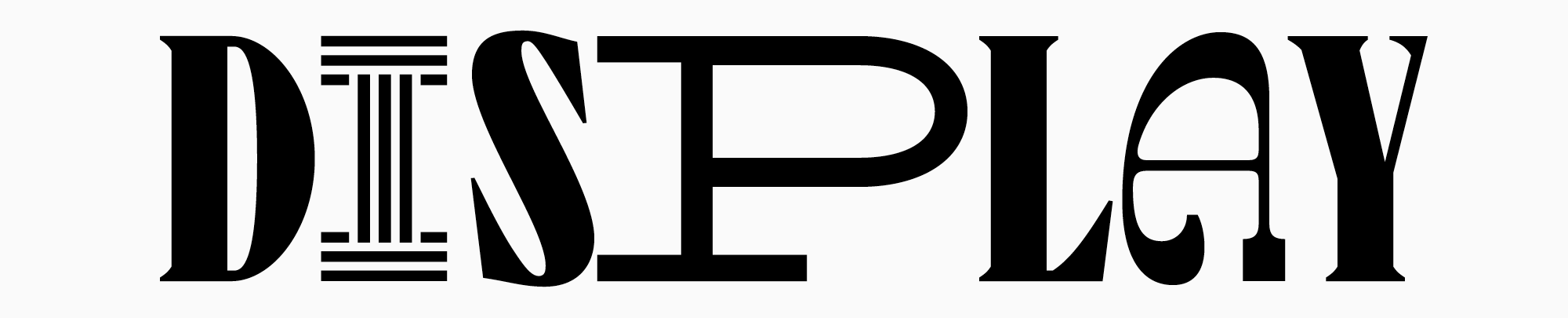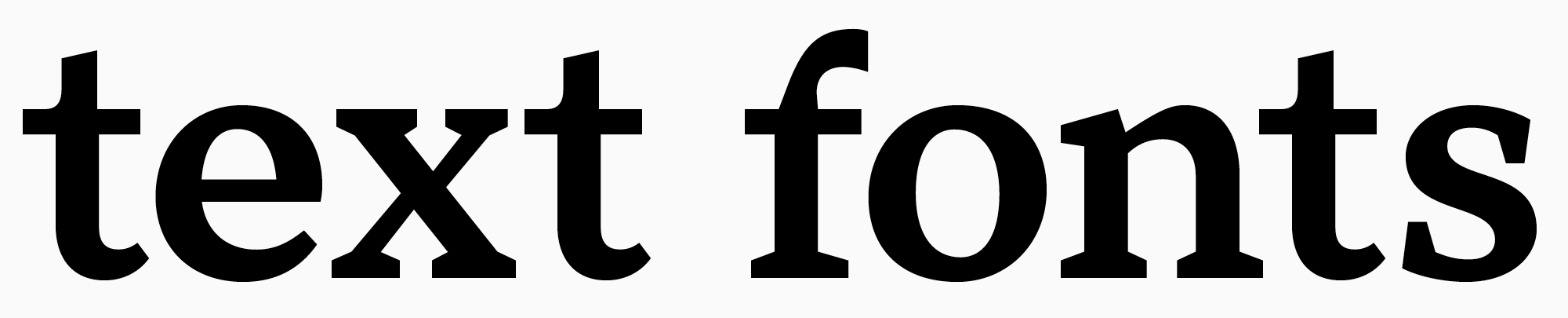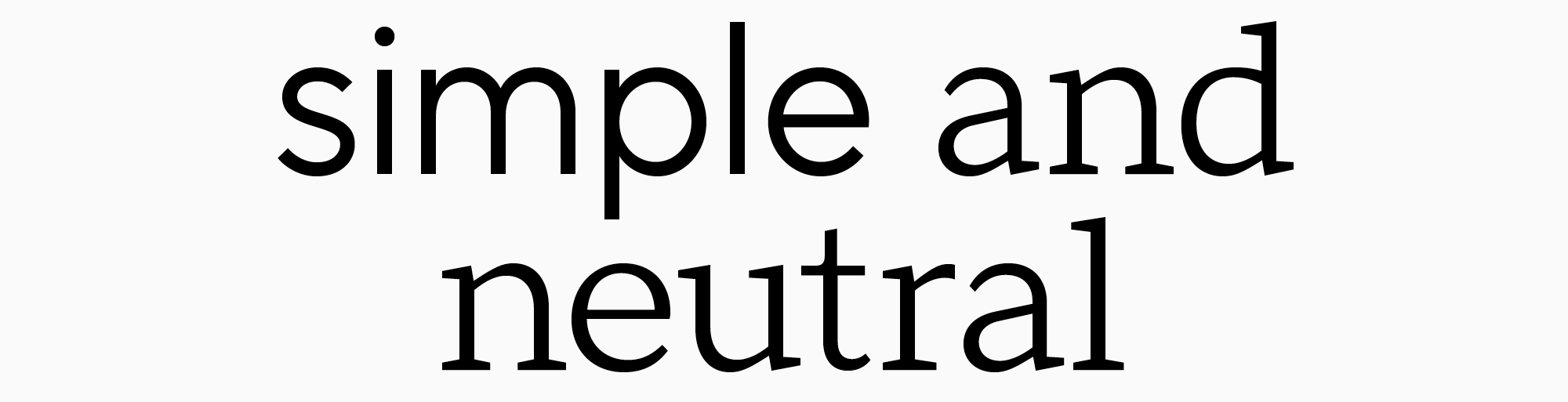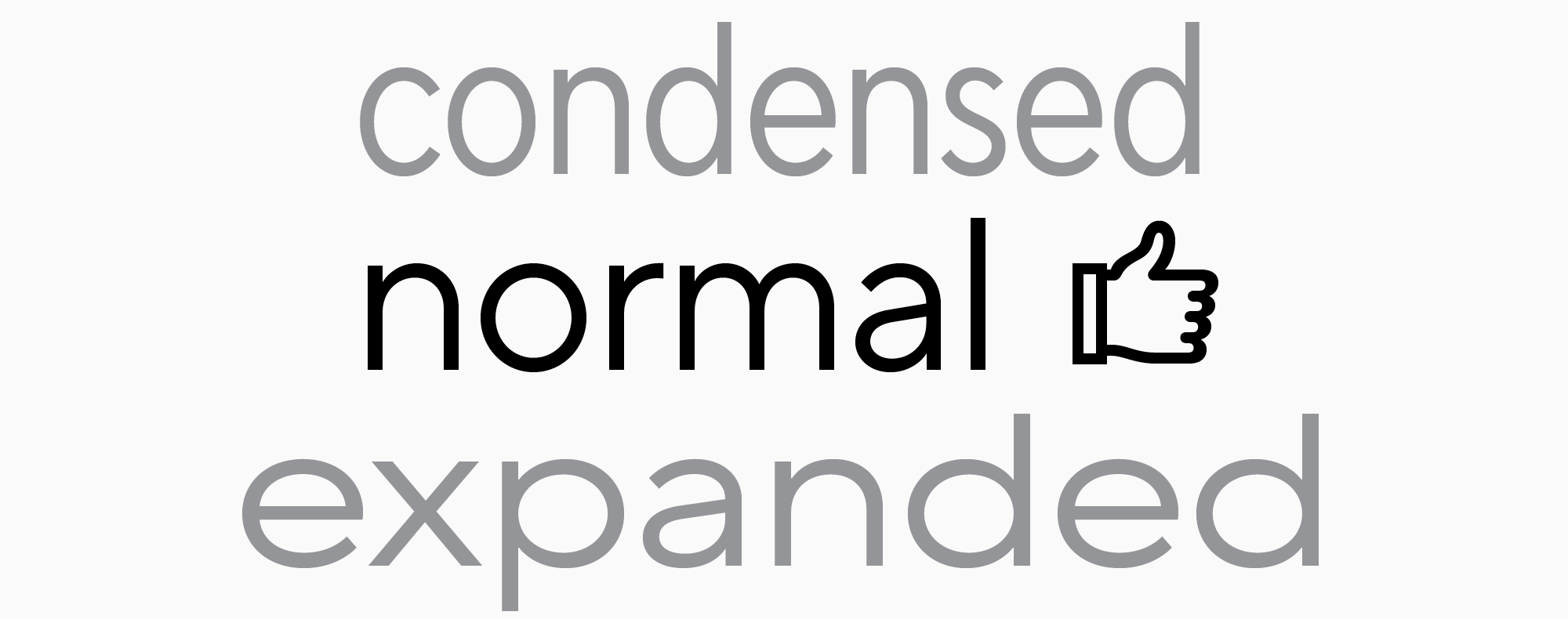
Какие шрифты лучше подходят для чтения? ТОП-10
Выбрать лучший шрифт для чтения — задача, которая возникает перед нами чаще, чем может показаться. Читабельный шрифт может понадобиться для масштабных проектов, таких как создание сайта, верстка книги или разработка мобильного приложения. Но также вопрос, какой шрифт выбрать для чтения, нередко возникает в более мелких, бытовых ситуациях: например, во время написания текста в «Ворд» и его печати на листе бумаги.
Какой шрифт наиболее удобен для чтения? От чего зависит читабельность шрифта? Какой шрифт лучше подойдет для чтения книг, а какие — для чтения с экрана? На эти и другие вопросы мы постарались ответить в этой статье.
Почему важно использовать удобные для чтения шрифты?
Представьте, что вы отправляете покупателю свой товар, в который вложили много сил. Вы красиво его упаковали и и обещали доставить как можно быстрее. Но курьер везет его очень долго, по пути роняет и пачкает. Содержание посылки остается неизменным, но покупатель тратит время и нервы на ожидание, а затем его впечатление окончательно портится при виде грязной, изорванной упаковки, которую он с трудом распаковывает. Скорее всего он больше не захочет ничего у вас заказывать.
И шрифт в этой аналогии — тот самый курьер. От него зависит, насколько легко и приятно пользователь будет воспринимать информацию, которую вы доносите до него с помощью текста. Одни шрифты будут читаться быстро и просто, другие — с трудом, отвлекая внимание от самой сути.
Это не значит, что одни шрифты однозначно хорошие, другие — однозначно плохие. Все зависит от того, где вы их используете: идеальный шрифт для баннера может не подойти для оформления веб-сайта, а лучший шрифт для верстки — оказаться неудачным для вывески.
Поэтому для начала давайте разберемся, какие шрифты лучше подходят для разных целей.
Какие шрифты лучше подходят для чтения?
Все шрифты по назначению можно разделить на акцидентные и текстовые.
Акцидентные отличаются ярким и выразительным характером, могут быть необычными и непривычными для глаза. Они привлекают к себе внимание и используются для акцентных надписей и заголовков (поэтому их часто называют заголовочными). Такие шрифты эффектно смотрятся в отдельных крупных надписях, но неудобны для массивов текста — глаз цепляется за отдельные буквы, мешая восприятию написанного. Они часто насыщены множеством деталей, которые интересно рассматривать в крупном кегле. В мелком же размере эти детали теряются, к тому же могут «размывать» буквы, делая текст грязным и трудно читаемым. Кроме того, обычно для них характерен высокий контраст, который делает их выразительными, но, опять же, менее читаемыми в маленьком кегле.
Текстовые же шрифты предназначены именно для набора больших массивов текста. Они более нейтральные и спокойные, оформлены лаконично, обладают низким контрастом и не имеют лишних деталей. Все это делает их более разборчивыми в мелком кегле и позволяет глазу легко скользить по тексту, не отвлекаясь на сами знаки. Кроме того, текстовые шрифты хорошо читаются в мелком кегле. Так что именно эта группа шрифтов нас сегодня интересует.
Существует представление о том, что шрифты без засечек лучше подходят для чтения, чем шрифты с засечками. Однако это не так: шрифты с засечками, или антиквы, вполне могут быть текстовыми, а засечки — помогать восприятию текста. Поэтому важно понимать, что же на самом деле влияет на читабельность шрифта.
Что делает шрифт удобочитаемым?
Здесь нужно разделить понятия «разборчивость» и «читабельность».
Когда мы говорим о разборчивости (legibility), имеется в виду четкость отдельных знаков и точность их начертания, которая влияет на легкость распознавания разных букв.
Читабельность (readability) же зависит от того, как знаки взаимодействуют между собой, то есть каким получается само тело текста при наборе. Это характеристика, указывающая на то, насколько удобно воспринимать массив текста.
В первую очередь, чтобы хорошо читаться, шрифт не должен быть сложным. Самый читабельный шрифт — простой и достаточно нейтральный. Излишние элементы будут размывать знаки в маленьком кегле, а слишком яркий характер может отвлекать внимание, мешая чтению.
Оптимальным для чтения шрифт делают скругленные контуры — они воспринимаются лучше, чем сквадраченные. Контраст штрихов должен быть достаточно выражен, но не слишком. Большую роль играют и пропорции — они должны быть нейтральными (когда ширина буквы приближена к высоте с небольшим преобладанием вертикали).
Толщина линий шрифта также очень важна — лучше всего читаются шрифты со средним весом. Поэтому для набора текста лучше всего выбирать регулярное начертание (Regular).
Ширина знаков оказывает непосредственное влияние на удобочитаемость — и здесь тоже стоит выбирать средний вариант. Так, в некоторых популярных гарнитурах TypeType есть несколько подсемейств. Знаки в подсемействе Normal имеют усредненную, «нормальную» ширину, наиболее удобную для восприятия текста. Также существуют, например, подсемейства Condensed, Compact, Normal, Expanded, Mono и другие.